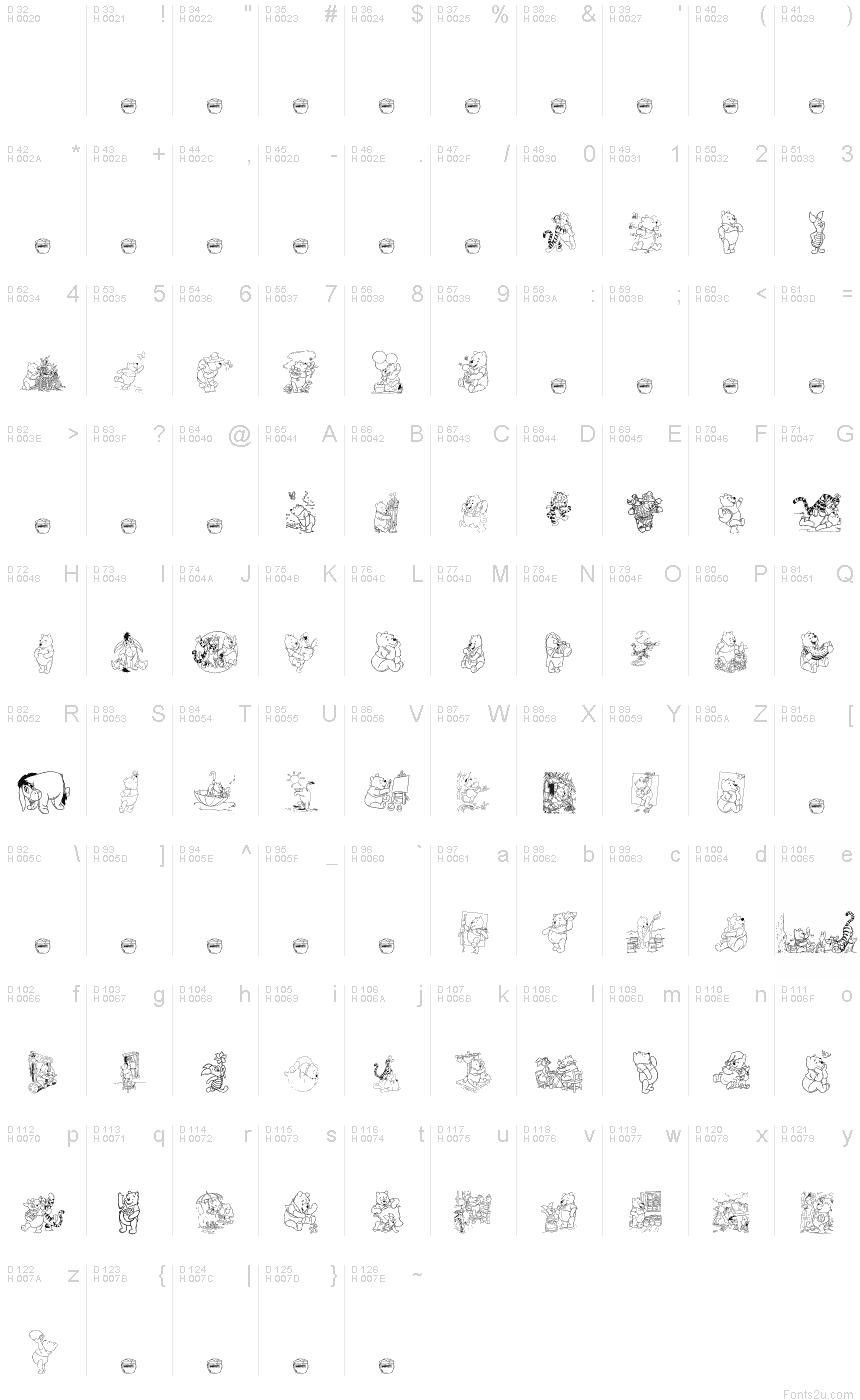
Disney's Pooh, de yellowyellow, es una tipografía de dingbats gratuita basada en dibujos suaves inspirados en libros de cuentos. Se caracteriza por sus formas redondeadas, contornos sueltos y ese aire cálido típico de las clásicas producciones de Disney. El set incluye desde posturas animales juguetonas hasta abejas y movimientos tiernos, logrando un estilo pícaro y desenfadado, pensado especialmente para composiciones decorativas donde la ilustración es la protagonista.
Esta fuente gratuita es ideal para invitaciones a fiestas infantiles, proyectos de scrapbooking, arte para habitaciones de niños o envoltorios temáticos, donde los personajes ayudan a transmitir el mensaje. Funciona de maravilla en pegatinas, títulos y pequeños detalles decorativos cuando buscas añadir ese toque amistoso y nostálgico del mundo de Pooh a tus diseños.